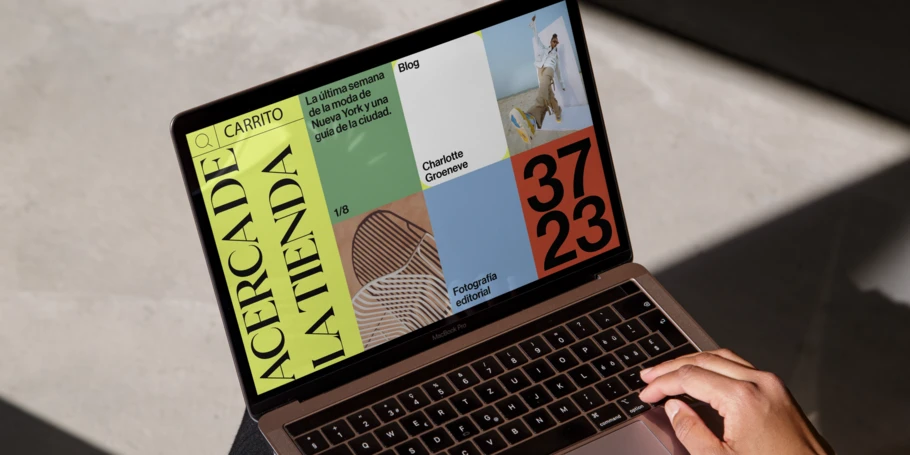
Cómo han cambiado las expectativas de los consumidores sobre la experiencia de usuario y cómo afecta al uso de tipografías.
« Los usuarios actuales se comportan de una manera diferente en Internet y esperan más de las marcas. »
Cómo han cambiado las expectativas de los consumidores y en qué te afecta.
Por si no te habías dado cuenta, el mundo y la cultura han vivido grandes cambios últimamente. Aun a riesgo de justificarlo todo con el COVID, es cierto que la pandemia ha hecho aflorar sensaciones duraderas de aislamiento y dado lugar a una mayor dependencia de las experiencias digitales.
Además, el cambio climático ha acelerado el interés de los consumidores por la biodiversidad y la sostenibilidad. Por último, la brutalidad policial ha desatado movimientos por los derechos sociales y aumentado la atención que prestan las marcas a la diversidad, la igualdad, las iniciativas de inclusión y el activismo. Sigue leyendo para comprender cómo influyen estos cambios en las expectativas sobre el diseño y la experiencia de usuario, y qué relación guardan con tu marca.
La pandemia ha cambiado las expectativas digitales de todo el mundo.
Entre los confinamientos, las clases desde casa y el cambio al teletrabajo por parte de una gran parte de la población, el tiempo que se pasa sin salir y usando pantallas ha aumentado en gran medida en los últimos años. Nos volvimos dependientes de unos dispositivos rectangulares de distintas formas y tamaños, y para muchos, las interacciones con las pantallas eran las únicas que tenían en todo el día. En muchos casos, esta situación hizo que la gente se sintiera más cómoda a la hora de comunicarse digitalmente con las marcas. Antes de la pandemia, el uso de mensajes para comunicarse con las marcas estaba en el quinto puesto en las preferencias de los consumidores para contactar con el servicio de atención al cliente, pero ahora ocupa el segundo lugar. Como respuesta a esta situación, las marcas más experimentadas pasaron de limitarse a ofrecer información de una forma fría a interesarse por maneras de acercarse, empatizar y buscar la complicidad de sus clientes.
El diseño experimentó un efecto dominó: las empresas encontraron formas de empatizar con los problemas del día a día del mundo a través de mensajes más amables y un diseño más agradable. Por primera vez, los consumidores ajenos a la comunidad del diseño empezaron a reconocer que la información que vemos en los espacios digitales suele estar creada con las mismas plantillas, fórmulas y tipos de letras. Los gestores de marcas y los equipos creativos se dieron cuenta de que la forma de nuestro mundo digital carecía de variedad, diversidad y humanidad.
La pandemia empujó a las marcas a lanzar más aplicaciones y nuevos servicios.
Antes de la pandemia, muchas marcas no tenían una experiencia digital integral; esa experiencia se limitaba meramente al aspecto y a la sensación. Lo bueno del diseño digital es el nivel de interacción, la forma que tenemos de mover el ratón, de responder a los menús y a las interacciones, y de atender las preguntas. Teniendo en cuenta todo esto, las marcas han empezado a diferenciarse más y a intentar ser más únicas que nunca. Un buen ejemplo en lo que respecta al diseño es la implementación de tipos de letras variables y cómo pueden adaptarse a todo tipo de situaciones.
Aunque se ponga en duda si trabajar desde casa aumenta la productividad o no, es innegable que eliminar el tiempo que se dedica a ir a la oficina y a estar allí ha hecho que multitud de personas sean mucho más eficientes, y todo esto ha aumentado sus expectativas de recibir respuestas y experiencias de forma más rápida o incluso instantánea. La gente está dispuesta a asumir más riesgos en virtud de la velocidad: prefiere recibir envíos en casa en lugar de pasar por las tiendas, aunque ello pueda poner en peligro la seguridad de su información financiera personal. Por su parte, las empresas han tenido que poner empeño en la personalización, la privacidad y las medidas de seguridad. Aunque las tipografías variables todavía no han llegado a la madurez, las fuentes variables ofrecen a las marcas la oportunidad de hablar con muchas voces diferentes, de proporcionar una experiencia de usuario más segmentada y de contar con perfiles de personalidad.
La catástrofe de la pandemia hizo aflorar un deseo colectivo de entretenimiento y evasión.
En un lapso de unos dos años, hemos pasado de comprar en Internet a entrar en tiendas digitales y probarnos ropa que vemos mediante píxeles. Las sensaciones de ansiedad y aislamiento, junto con el tiempo que pasamos en casa, han hecho que los consumidores se sientan más cómodos con las nuevas tecnologías y las experiencias virtuales. Si quieres pruebas, basta con mirar el metaverso, un entorno en el que se están invirtiendo muchos fondos y donde se está investigando desde el punto de vista creativo. Los límites entre lo real y lo virtual están cambiando, y se espera que las marcas diseñen experiencias que se ajusten a estos espacios:
Hay multitud de factores que conducen al auge del activismo de las marcas.
Volvamos a la realidad. Como mencionábamos antes, estamos un poco más concienciados con causas como la sostenibilidad, la diversidad, la igualdad y la inclusión, y eso está haciendo emerger el activismo de las marcas. No es ninguna sorpresa que a la gente le importen más estas cosas que antes; lo relevante es que los consumidores se ven más influidos por el nivel de activismo de las marcas que por el propósito que las mueve. Buscan afinidad con las firmas que intentan hacer del mundo un lugar más justo, y eso va más allá de la misión que proclaman. Queremos ver cómo se implican para resolver los problemas de la sociedad.
Si vamos un poco más allá, vemos que a los consumidores les importa la esencia de las marcas, es decir, cuáles son los principios que las mueven. Y esos principios se definen desde los puestos más altos. No se trata simplemente de ideales, para los consumidores eso no basta. Deben ser valores genuinos y apasionantes, y estar presentes en todos los puntos de contacto con las marcas. Veamos un ejemplo real de la mano del director ejecutivo creativo de Monotype, Phil Garnham: «Esta mañana me suscribí a un nuevo producto sostenible de lavado por la excesiva cantidad de residuos plásticos que generan las principales marcas de los supermercados», comenta Garnham. «Se anunciaba en las redes sociales. Lo que me resultó atractivo no fue la estética del anuncio, sino el hecho de que me daba la oportunidad de ser más cívico y de ahorrar dinero. Hacía un uso eficiente del mundo digital y daba la sensación de ayudar a hacer el bien, por así decirlo». El hecho de usar contenido nativo en un espacio que ya frecuentaba, como Instagram, junto con la utilidad de la experiencia digital y la posibilidad de hacer el bien fue suficiente para que Garnham hiciera clic en «Suscribirme». Un ejemplo real que muestra por qué es importante comprometerse con una misión.
¿Cuál es la relación entre las tendencias y las expectativas de los consumidores?
El tono y las expectativas de la generación Z no se limitan a sus formas de cortarse el pelo y a sus gustos en los vaqueros, sino que influyen en toda la población. Dado que esta generación ha crecido en un momento difícil, puede decirse que es la primera en exigir más a las empresas con las que se siente identificada y a las que compra sus productos. Estamos siendo testigos de cómo la perspectiva consciente de los consumidores llega al liderazgo de las empresas.
No es fácil determinar una relación de causa y efecto con las tendencias y las expectativas de los consumidores. Esta relación es más bien como un remolino, y las influencias culturales también contribuyen a definir las expectativas y a generar tendencias. Es como lo del huevo y la gallina: hay errores creativos que tienen resultados positivos y hay tendencias que surgen de la necesidad, con el todopoderoso encargo creativo. Por un lado, los consumidores están condicionados por los productos y servicios disponibles, aunque también disfrutan si hay algún elemento sorprendente en el diseño y la identidad de marca. Pensemos por ejemplo en Habito, la empresa de hipotecas que se menciona en este informe de tendencias tipográficas de 2022, cuya sorprendente identidad de marca incluye una paleta de colores oníricos y unos mensajes atrevidos que ayudaron a la empresa a diferenciarse de la competencia en un sector muy homogéneo. Superunion se encargó de redefinir la marca de Hermes como Evri, un caso que destaca también por el uso de un logo vivo, algo nunca visto. El logotipo incluye una tipografía variable personalizada de Monotype Studio con más de 190 000 variaciones.
Por supuesto, no todas las marcas pueden ni deben lanzarse a por un logo vivo, desarrollado con este tipo de tecnología de tipografía variable, pero hay varias fases de madurez digital en el proceso de diseño y la experiencia de usuario que deben tenerse en cuenta. En un extremo del espectro de madurez digital tenemos a las marcas que usan herramientas de código abierto, fuentes gratuitas y plantillas existentes para sus sitios web o aplicaciones. Esto no significa automáticamente que se trate de una estrategia de bajo presupuesto y, si se hace bien, no tiene por qué notarse mientras la experiencia funcione de forma clara y fluida. En el otro extremo del espectro digital están las identidades de marca más únicas y matizadas, como las de Habito y Evri.
¿Qué es lo esencial para seguir siendo competitivos?
El crecimiento digital de los últimos años ha definido claramente y alimentado las expectativas en torno a la experiencia interactiva de las marcas. Las más avanzadas han creado modelos de suscripción para ajustarse a la frecuencia con la que las necesitas, y lo han hecho siendo empáticas. Por lo general, gracias a la democratización de la tecnología y a la disponibilidad de herramientas web y de diseño, ahora el diseño y la experiencia de usuario en su mayor parte son de calidad y coherentes en todos los ámbitos. Una de las tendencias que hemos observado es que está surgiendo un nuevo estilo universal: la simplicidad en el diseño está presente en las marcas online modernas y parece que casi estamos volviendo al minimalismo de las empresas emergentes de hace cinco años. Son muchas las marcas que están apostando por una tipografía limpia y de estilo geométrico.
Las empresas que van más allá de lo establecido son las que visualizan el lugar único que ocupan entre la competencia con experiencias web y de aplicaciones hechas a medida, aquellas que experimentan con espacios emergentes, como el metaverso, y que usan elementos bien diseñados, como la tipografía personalizada, una identidad de marca sorprendente y un tono humano. Lo que tienen en común todas estas decisiones acertadas es haber elegido bien las tipografías. A la hora de escoger una fuente para tu marca o campaña en una biblioteca, al modificar una con la que ya cuentas o al encargar un tipo de letra personalizada, debes asegurarte de que tu mensaje se represente correctamente y de que tu solución esté a la altura en lo que respecta a las cuestiones técnicas.
Dicho esto, no hay nada que sea esencial. El mínimo lo marca el mercado en el que operas y las marcas que existen en torno a él. Como creativo o responsable de marca, la única métrica por la que debes regirte es la de crear las experiencias de diseño más atractivas e innovadoras que puedas ofrecer a tus clientes. Si puedes crear algo nuevo o aportar tu toque para que una marca parezca nueva y única, conseguirás que destaque. Para mejorarlo todavía más, añade una capa de significado con una narrativa creativa y mensajes personalizados que lleguen a tus clientes. Será en ese momento cuando te des cuenta de que has clavado tu encargo creativo y alcanzado tus expectativas o las de tus clientes al hacer que la historia de la marca triunfe.